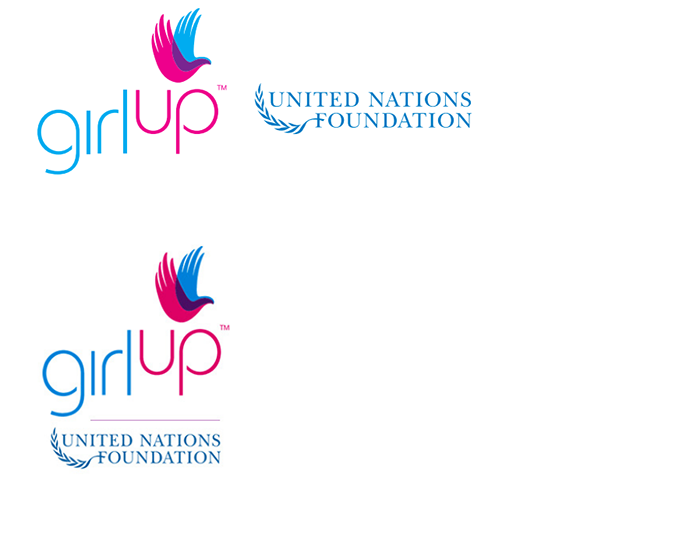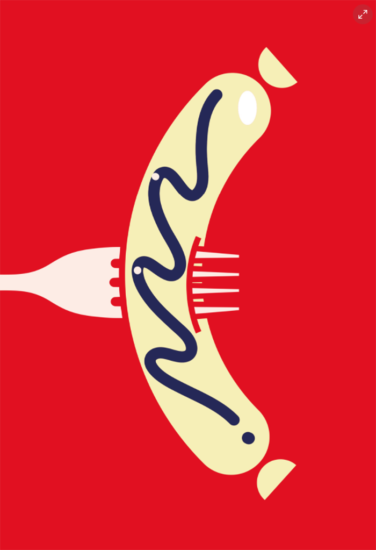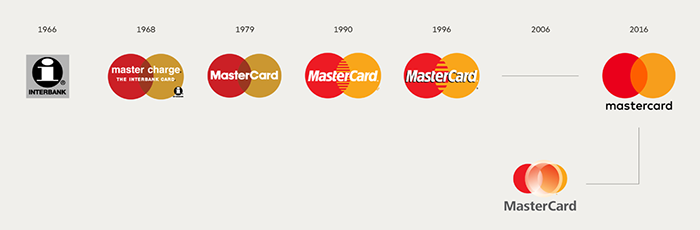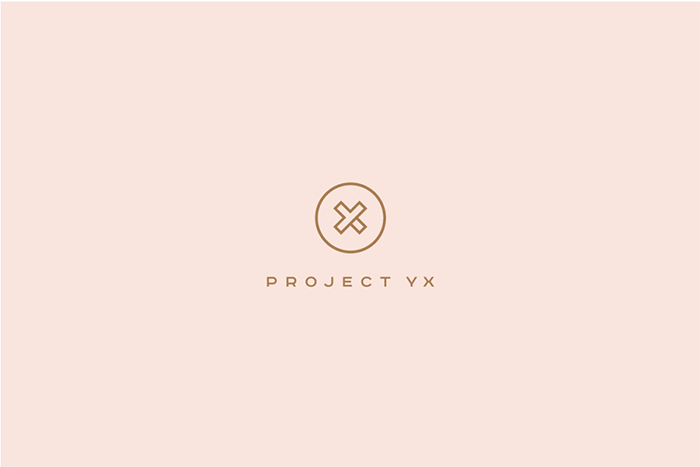
평범한 로고와 탁월한 로고의 차이
헬스 잡지 페이지를 넘기다 보면 나이키 로고를 자주 보게 됩니다. 마스터카드 광고판을 올려다 보면 어김없이 두 개의 원이 보입니다. 여러분은 이러한 브랜드를 인식할 수 있습니까? 물론 그럴 것입니다. 브랜드를 한눈에 알아보게 하는 것은 무엇 때문일까요?
첫째, 로고 자체가 브랜드 아이덴티티가 아니라 브랜드 아이덴티티의 일부라는 것을 이해해야 합니다. 브랜드 아이덴티티를 구성하는 모든 요소와 이들 요소가 로고와 함께 시각적으로 어울려 함축적이고 효과적인 브랜드 아이덴티티를 형성하는 방법을 생각해보십시오.
신규 브랜드를 만들거나 잘 알려진 기존 브랜드를 통해 창의성을 발휘하려는 경우 효과성이 우수한 로고가 해답입니다. 컨텍스트와 스타일은 해마다 다르지만 로고를 디자인 할 때 지침이 되는 원칙과 모범 사례는 달라지지 않습니다.
효과적인 로고가 갖추어야 하는 요소를 떠올릴 때, 반드시 염두에 두어야 하는 몇 가지를 소개합니다.
매력적인 로고 제작을 위한 디자인 원칙
1. 브랜드에 대한 시각적 전략을 수립할 것.
최근 로고 디자인의 접근 방식은 브랜드 전반에서 일관적인 전체 시스템, 즉 기본 마크, 이차적 마크, 타이포그래피, 색상 견본을 만드는 것입니다. 로고는 FedEx, 3M 또는 Coca-Cola와 같이 별도의 아이콘 없이 타이포그래피로 구성된 로고인 워드마크와 애플, 나이키, 타겟 등의 회화적이거나 추상적인 마크가 있습니다.
로고 시스템은 로고를 개별적으로 사용하는 경우 또는 락업(lockup)(아이콘, 워드마크, 태그라인과 같은 여러 브랜드 요소를 그룹화한 것)을 사용하는 경우에 대한 가이드라인과 함께 이러한 모든 요소를 포함하는 개념입니다. 로고는 대부분 다중적 구조이며 컨텍스트에서 의미가 부여되므로 핵심은 시각적인 브랜드 시스템이 얼마나 많이 또는 적게 의사 소통하는지에 대해 생각하는 것입니다.
2. 다양한 환경에서 사용 가능한 로고여야 할 것.
최고의 로고는 기억에 남아야 하지만 다양한 최첨단 환경과 디지털 플랫폼, 커뮤니케이션 채널 및 물리적 개체에서도 제 기능을 발휘해야 합니다. 탁월한 로고는 손쉽게 크기를 변경하여 다양한 환경에서 재생산될 수 있어야 하므로 확장이 가능하고 반응형(모바일 기반 디자인의 경우)이면서 다양한 크기, 모양, 차원 및 애플리케이션에서 식별이 가능해야 합니다.
3. 복잡함 속에서 핵심을 찾을 것.
컬러 또는 흑백으로 만들 것인가? 정교하게 또는 간결하게 제작할 것인가? 추상적 또는 직설적으로 만들 것인가? 등을 고려합니다. 최고의 로고라면 한두 가지의 색상으로 압축되며 간편하게 크기를 조정할 수 있어야 합니다. 그렇지 않으면 너무 복잡해지고 식별하기 어렵거나 기억에 남지 않을 것입니다. 로고가 한 가지 색상이어야 한다는 규칙은 없지만, 색상은 로고가 시각적으로 적합한 복잡성의 수준에 있는지의 여부를 나타낼 수 있습니다.
로고의 효용성을 테스트하는 한 가지 방식은 야구 모자에 로고를 박음질하여 재생산하는 방법을 머릿속에 그려보는 것입니다. 로고가 야구 모자에 무난하게 표현될 것 같으면 대부분의 모든 애플리케이션에서도 간단히 보여질 수 있을 것입니다.
4. 트렌드를 주시하되 시간이 지나도 건재한 로고를 목표로 할 것.
지금은 ‘플랫’한 디자인과 미니멀리즘을 추구하는 접근 방식이 인기를 누리고 있지만 10년이 지난 후에는 디테일이 추가된 다채로운 색상의 로고가 트렌드로 부상할 수 있습니다. 디자인 트렌드는 움직이는 창을 통해 보여지는 것으로, 시대를 초월한 로고는 과거에 만들어진 로고와 차별화되어 시각적으로 눈에 띕니다.
비핸스(Behance.net)와 같은 사이트를 사용하여 현재 유행하는 디자인 트렌드를 파악함은 물론 시대를 초월한 탁월한 로고에 주목하여 디자인이 당대의 취향을 반영하고 시간이 지나도 굳건할 수 있는 방법을 살펴보시기 바랍니다.
▲ 미니멀리즘에 착안한 로고 (이미지 출처: Martin Servantes)
4. 독창적이어야 할 것.
브랜드 발굴을 통한 시각적 아이덴티티 제작을 고심할 때 디자이너는 시간이 지남에 따라 건재한 영향력을 과시하는 로고를 만들고 싶어할 것입니다. 로고 디자인은 상표로서의 독창성을 충분히 확보한 다음에 디자인 단계에 돌입해야 합니다. 이는 다른 브랜드가 유사한 모양을 채택하여 기존 고객에게 혼동을 주거나 고객을 탈취하는 결과를 방지하기 위해서도 중요한 일입니다.
클라이언트의 시각적 아이덴티티 니즈를 충족하기 위한 모범 사례
1. 크리에이티브 개요서 제작
훌륭한 디자인의 대부분은 올바른 질문을 던지는 것에서 출발합니다. 로고 디자인의 경우 구체적이면서도 간결한 크리에이티브 개요서를 개발하는 것은 훌륭한 시작이 됩니다. 크리에이티브 개요서를 통해 다음 사항을 발견할 수 있어야 합니다.
– 시각적으로 의사 소통할 기업의 퍼스낼리티. 퍼스낼리티가 유머러스하거나 진지한지 여부. 다이내믹하고 에너지 넘치는지 또는 안정되고 차분한지 여부
– 대상 고객 정의 및 대상 고객의 시각적 선호도 이해. 대상 고객 및 고객의 취향
– 경쟁사의 로고와 디자인 검토 및 자사 브랜드의 차별화 방안
– 로고를 적용할 다양한 앱에 대한 이해. 로고를 건물 사이니지로 전환해야 하는지 여부. 셔츠에 박음질로 새겨 넣을지 여부. 앱 아이콘 사용 여부
– 브랜드에 대한 비전을 이해하고 회사의 ‘얼굴’이 될 로고에 대한 주인 의식을 제공하기 위한 주요 이해 관계자 인터뷰
2. 개념 개발
대상 고객을 이해했다면 무드 보드(mood board)를 사용해 브랜드를 위한 시각적 방향을 정의하면 도움이 됩니다. 무드 보드란 제작하려는 로고의 룩앤필을 나타내는 모든 시각적 예시를 한데 모은 것입니다. 아이디어 스케치를 시작할 때 첫 번째 괜찮은 콘셉트에 너무 집착하지 말아야 합니다. 양적으로도 많은 다양한 디자인 제작물에서 출발하여 최선의 노력을 기울여 모든 가능성을 타진한 이후에 최상의 디자인을 추려내어 세부적으로 다듬어야 합니다.
3. 세부 조정
서너 개의 아이디어를 간추린 다음에는 원본 디자인을 세부적으로 다듬고 반복적인 작업을 수행하는 데에 시간을 투자합니다. 이 프로세스를 너무 급하게 진행하지 마십시오. 많은 디자이너가 디자인 프로젝트에서 잠시 물러서 보다 객관적인 ‘새로운 시각’으로 디자인을 바라보는 것이 작업에 도움이 된다고 말합니다. 전혀 연관성이 없을 것 같은 뜻밖의 장소에서 평범한 디자인에 영감을 입힐 수 있습니다.
4. 디자인 사전 테스트
공략 표본 집단에 속하는 다양한 사람들에게 로고를 보내 솔직한 반응을 들어 보는 것입니다. 창작물을 검토할 때 호의적이며 예의상 긍정적으로 답하는 사람들의 본심을 간파하기란 어려운 일이지만, 반응을 살피는 것은 성공을 위한 필수 단계입니다. 익명으로 수행하는 웹 기반 설문조사를 고려해볼 수 있습니다. 또한 유용한 피드백과 그렇지 않은 피드백을 구분할 수 있어야 합니다. 유용한 피드백은 로고가 브랜드 아이덴티티를 잘 전달하고 있는지와 브랜드에 대한 사용자의 느낌을 평가하게 될 것입니다.
사람들의 개인적인 취향과 디자인의 객관적인 효과를 구분해야 합니다. 디자인의 효과에 집중된 피드백 질문(예: 로고만을 고려했을 때 구매하고 싶은 충동이 드는 회사는 어느 회사입니까?)은 개인적 취향에 치우친 질문(예: 선호하는 색상은 어느 색상입니까?)보다 바람직합니다.
간편한 로고 제작을 위한 사용자 친화적인 툴
1. 클릭, 캡처, 제작.
무료 모바일 앱인 어도비 캡처 CC(Adobe Capture CC)를 사용하면 영감을 얻은 곳에서 바로 촬영하고 이를 바탕으로 로고 제작이 가능한 모양으로 전환할 수 있습니다. 이 모양을 크리에이티브 클라우드에 저장하여 어도비 일러스트레이터 CC에서 계속해서 로고 작업을 이어가면 됩니다.
2. 참조 이미지 사용.
복잡한 아트 디자인이라도 사각형, 삼각형 및 원과 같은 기본 모양을 활용하면 쉽게 아트웍을 만들 수 있습니다. 어도비 스톡(Adobe Stock)을 사용할 경우 벡터 아트 파일을 다운로드한 다음 원본 디자인의 참조 이미지로 사용하여 어도비 일러스트레이터 CC에서 필요에 맞게 변경할 수 있습니다. 어도비 일러스트레이터 CC에서 색상을 입히고 프로젝트를 세부적으로 다듬은 다음 간편한 기능을 활용하여 텍스트를 추가하여 로고 작업을 마무리합니다.
3. 파일 공유.
최종 로고 파일 및 가이드라인을 흔히 사용하는 파일 포맷으로 CC 라이브러리와 같이 팀이 쉽게 이용할 수 있는 위치에 저장합니다.
고객에게 만족을 주는 브랜드 로고를 디자인하는 것은 복잡하지 않아도 됩니다. 몇 개만의 유용한 팁, 적합한 툴, 그리고 창의적인 영감만으로도 독창적인 로고를 손쉽게 만들 수 있습니다.